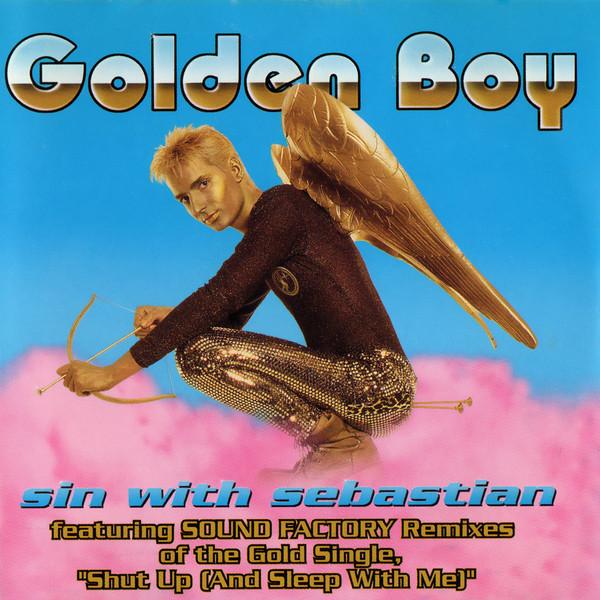
Sin with Sebastian Schrift
Liebes Forum,
ich suche folgende Schrift. Zu sehen auf den Cd und Vinyl Covern des Künstlers Sin With Sebastian.
Erste Single mit dieser Schrift: 1995
Kommt aus Deutschland.
Ich suche möglichst diese oder eine ähnliche Schrift. Darf auch was kosten.
Das sieht nach der Serpentine aus:
Typeface:	Serpentine
Designer:	Dick Jensen
Year:		1972, 1990
Originally designed by Dick Jensen for
Visual Graphics Corporation in 1972.
Der war zwar schneller, der bertel, lag dabei aber nicht ganz richtig. Deine Vermutung "Serpentine D" kommt dem Ganzen schon näher! :gimmifive:
Dass es die Sans ist, glaube ich nicht, auf dem Cover meine ich schon Serifen zu sehen.
Je nach Abbildung könnte es die Sans sein, aber auf einigen der Abbildungen scheidet diese definitiv aus. Bei der Qualität der Scans ist am Ende doch keine ganz sichere Aussage möglich. Für mich war die Serpentine D nach meinen Unterlagen am nächsten ... Aber das war auch nur geraten.
PS: Die Serpentine Italic ist/war eine typische Schrift für Speditionen und ggf. Busreiseunternehmen.
die Abbildungen sind alle von der gleichen Vorlage, dachte die ersten beiden Bilder sind aus einer anderen Quelle.
Dann sollte es natürlich die Serpentine Serif sein.